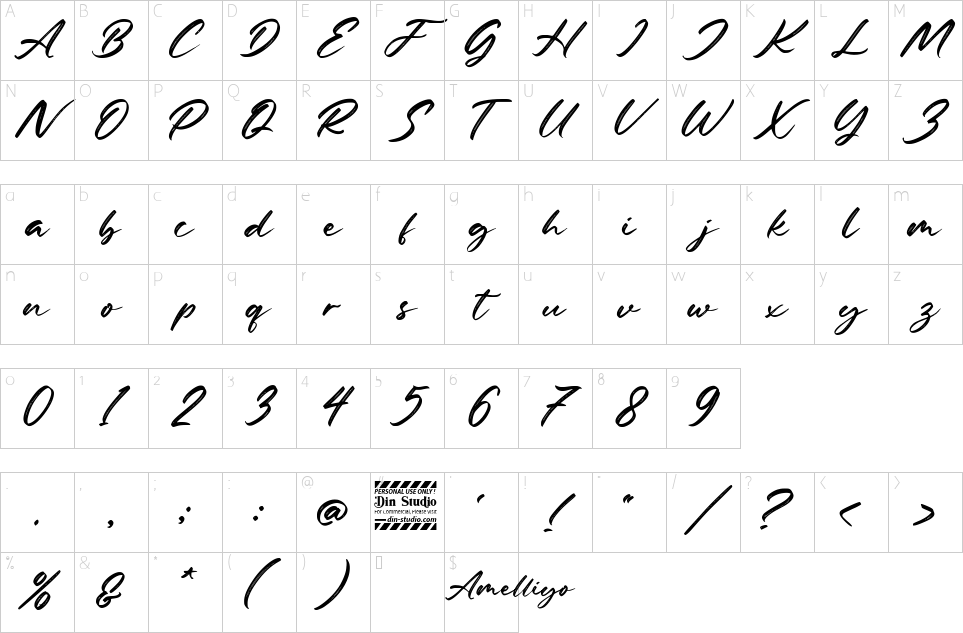
Amelliyo Font – Fonte Grátis
Amelliyo Font
Aqui está uma descrição envolvente e natural para a página de download da fonte ‘Amelliyo Font’: Amelliyo é uma fonte moderna e elegante, perfeita para aqueles que buscam uma solução que combine simplicidade e personalidade. Desenvolvida por Donis Miftahudin, a fonte apresenta uma arquitetura minimalista que combina harmoniosamente com diversos estilos de design. Seja para uso em materiais de mídia impressa, site ou aplicativos móveis, Amelliyo oferece uma experiência visual fluida e agradável aos olhos. Com 349 downloads, a fonte já ganhou reconhecimento e valor entre os designers e criativos. Instale-a em seu sistema e transforme o visual de seus projetos em algo único e atraente.
Mapa de caracteres da fonte Amelliyo Font